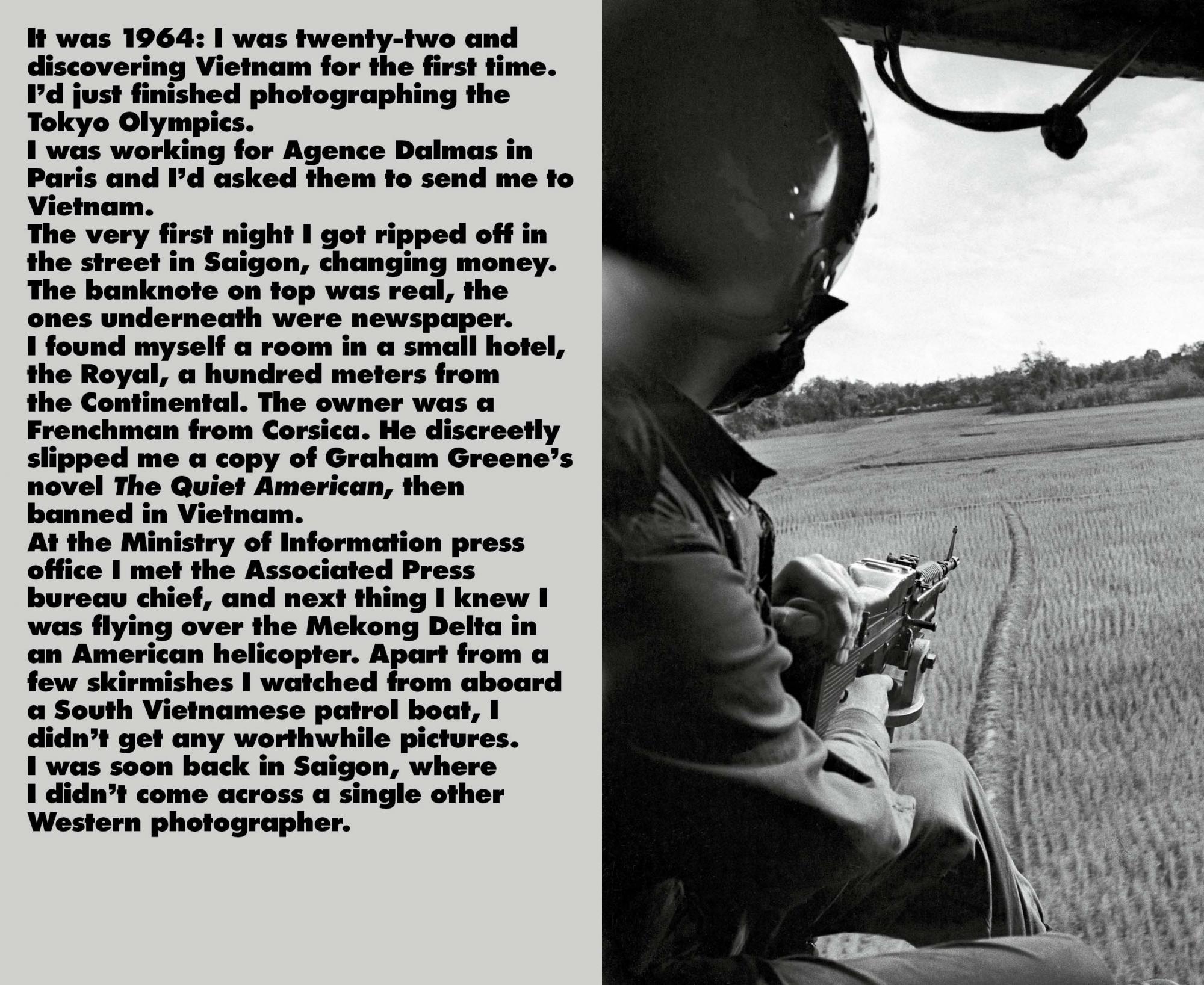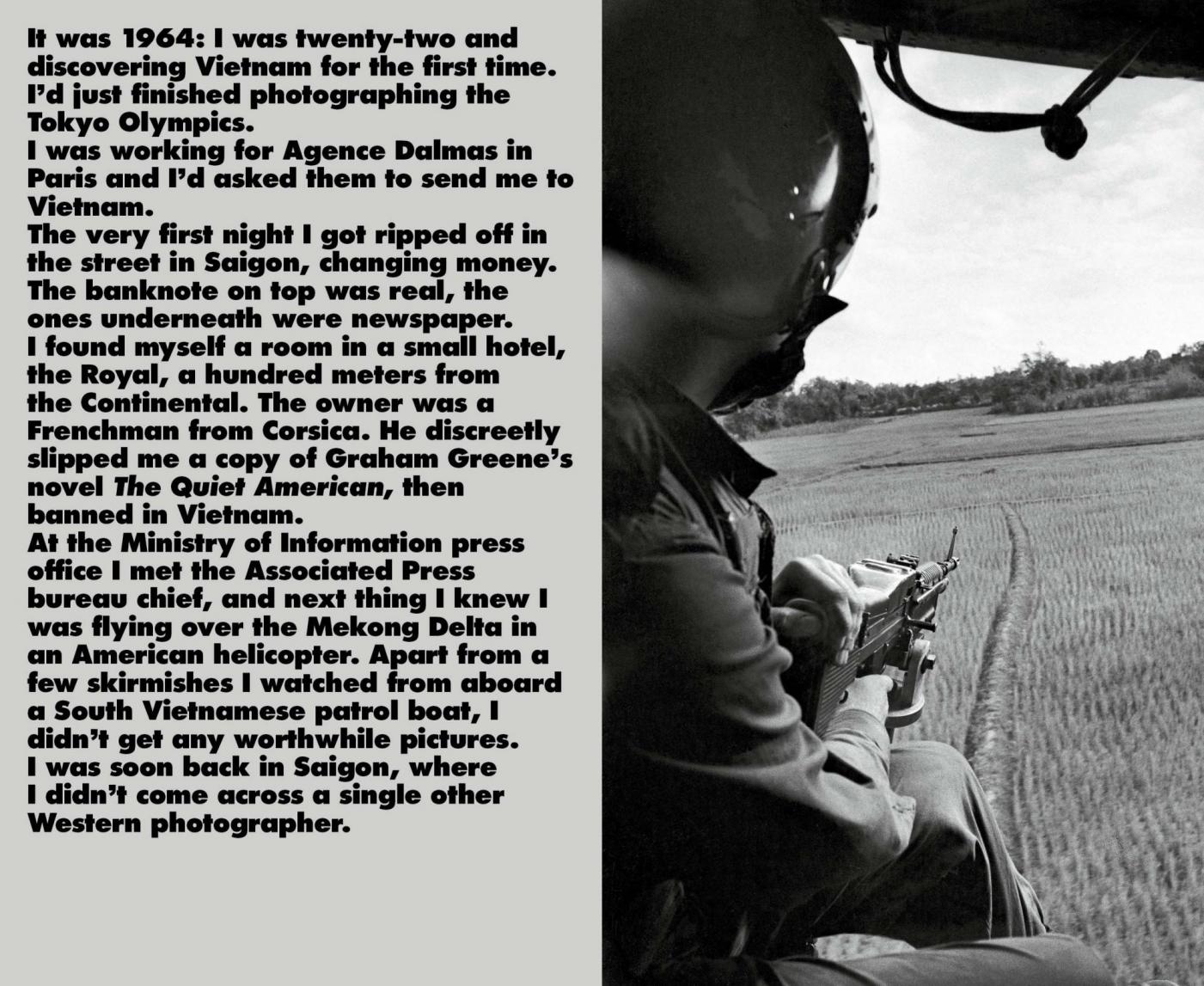
Schriftart gesucht aus Buch Adieu Saigon
habe vor längerer Zeit ein Buch erworben von Steidl.
Es ist Ein Buch über den Fotografen Raymond Depardon und es trägt den Titel "Adieu Saigon".
Publiziert wurde das Buch im Jahr 2015.
Da ich gerade meine Diplomarbeit schreibe und mich diese Schrift so fasziniert, würde ich gerne wissen wie sie heißt und ob jemand eine alternative günstige vielleicht auch kostenlose Alternative kennt, die dieser Schrift nahe kommt.
Futura.
Extra Bold, Black, Extra Black, irgendeiner dieser Schnitte.
Wenn es die ganze Schriftfamilie sein soll, ist die Futura Futuris (Paratype) am unteren Ende des Preisspektrums. Ich weiß nicht, inwiefern diese sich von Paratypes »normaler« Futura unterscheidet.
Letztlich ist nur Futura wirklich Futura … aber in die Kategorie »Geometrische Serifenlose« fallen natürlich noch zahllose andere Schriften:
Darunter auch einige eher günstige:
urw Geometric
Averta Standard (die Variante ohne Griechisch und Kyrillisch ist am günstigsten):
Und nicht ganz so »Extra«, aber zumindest »Bold« ist die Spartan, die es in der kostenlosen Version der League of Moveable Type gibt:
Die Aversa schaut auch ziemlich gut aus. :-)